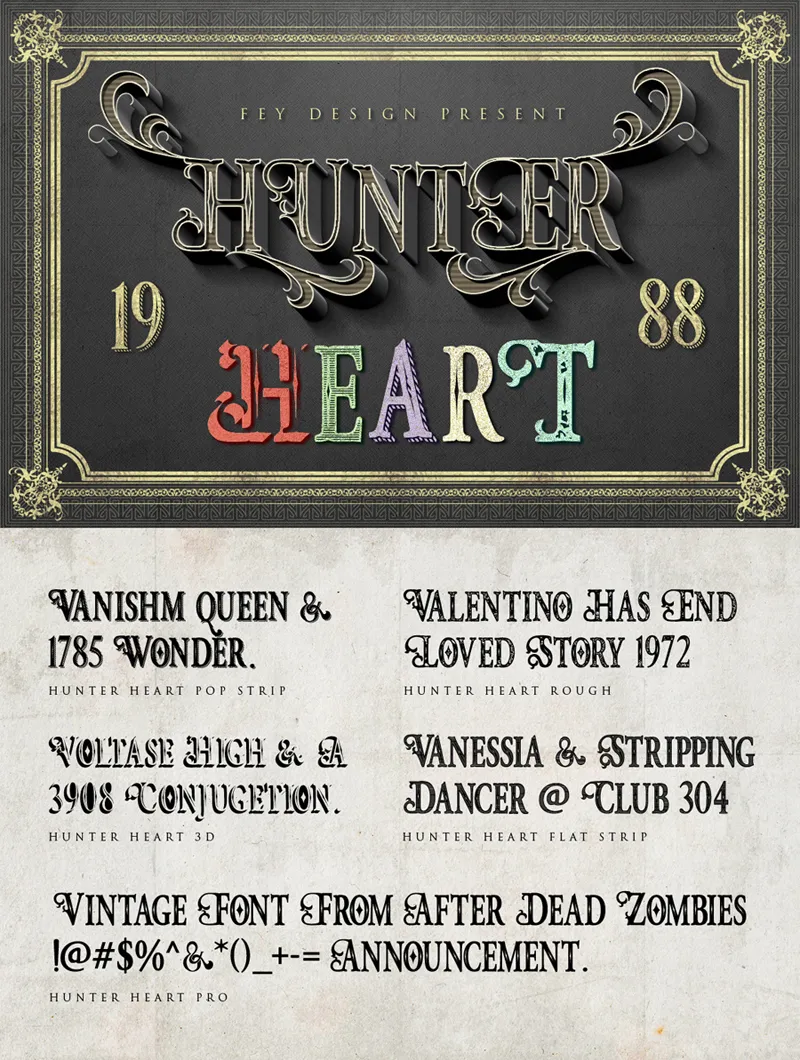
A fonte Hunter Heart é perfeita para quem busca uma tipografia que transmite uma sensação de conforto e simplicidade ao mesmo tempo. Com a elegância suave das linhas curvas e as formas redondas, essa fonte convida para um uso em qualquer projeto da sua marca. Sujeitável tanto aos títulos quanto aos textos detalhados, Hunter Heart é uma opção perfeita para quem busca um estilo diferente que ainda se mantém acessível e envolvente. Aproveite ao máximo suas possibilidades com o Full Version comercial de uso da fonte, disponível em nosso site www.creativemarket.com/feydesign, onde também você pode encontrar outras opções criativas de designer.